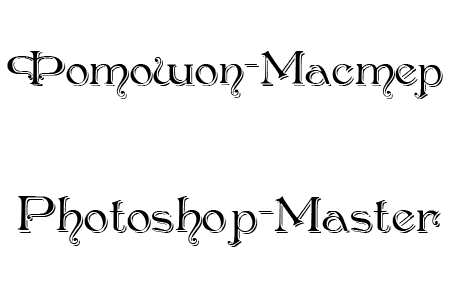
Изысканно!
Прекрасная обводочка))
Очень красиво. Уже вовсю использую)))
Оригинальный шрифт
Оригинальный шрифт, спасибо, пригодится))
Классный шрифт я как раз такой и искал для надписи на шапке сайта
Шрифт замечательный! Спасибо!
Обожаю в шрифтах всякие загагулинки.СПАСИБО!
Спасибо, прекрасный шрифт.